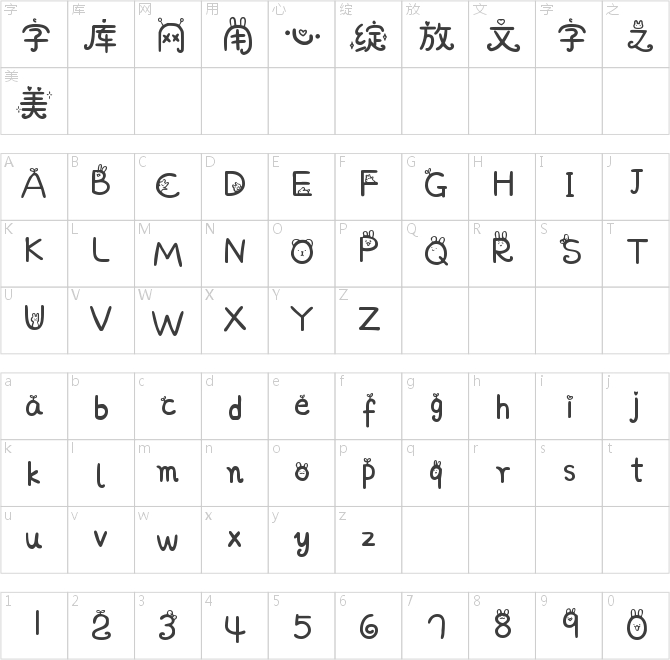
千圖小兔體是千圖網(wǎng)聯(lián)合國內(nèi)專業(yè)字體設(shè)計機構(gòu)iFonts共同發(fā)布的一款萌系創(chuàng)意字體,歷時半年多悉心打磨完成。向所有千圖網(wǎng)用戶開放免費下載。將可愛的千小兔融入字體設(shè)計中,盡顯年輕、活力與俏皮,適用于可愛、少女風的海報、店招等場景。
千圖小兔體字體QTxiaotu字庫是一款讓人賞心悅目、百看不厭的中文字體,適合各類廣告和產(chǎn)品包裝設(shè)計應用,字體大小5.25MB,格式為ttf字體,上傳用戶是快霸中國,作者/版權(quán)方為千圖/iFonts?